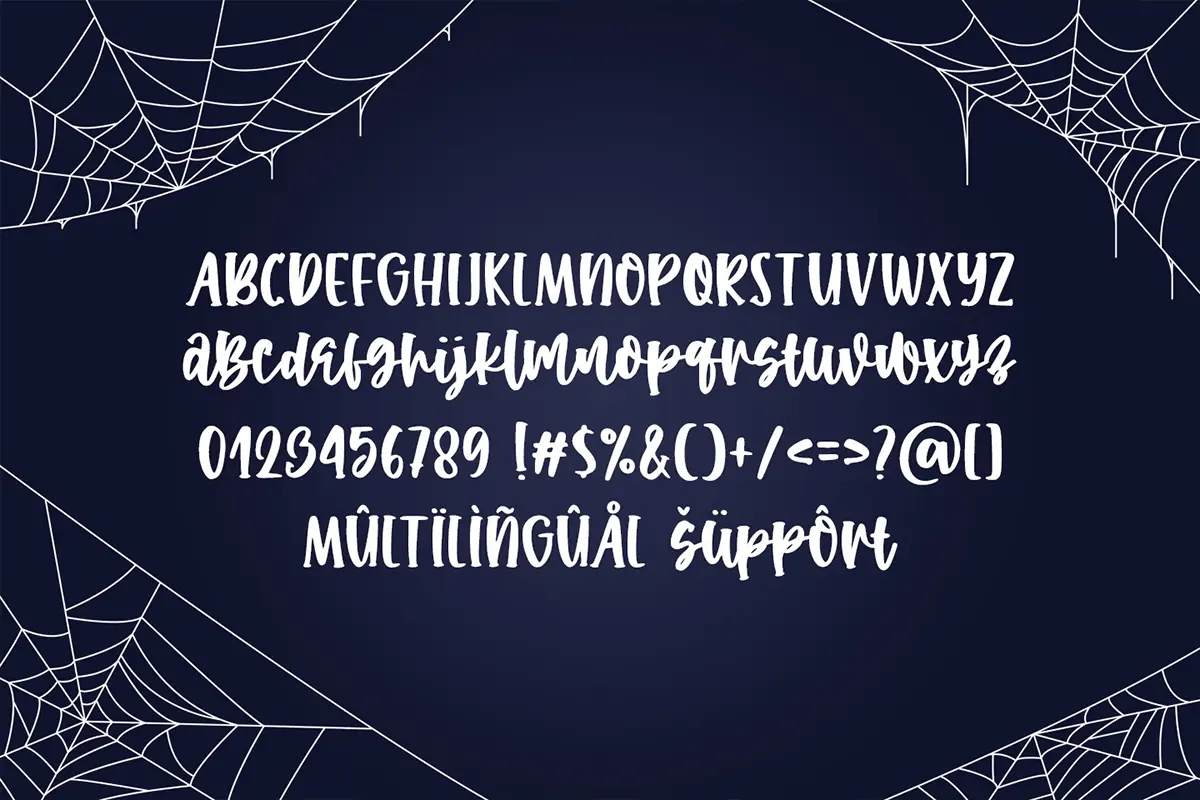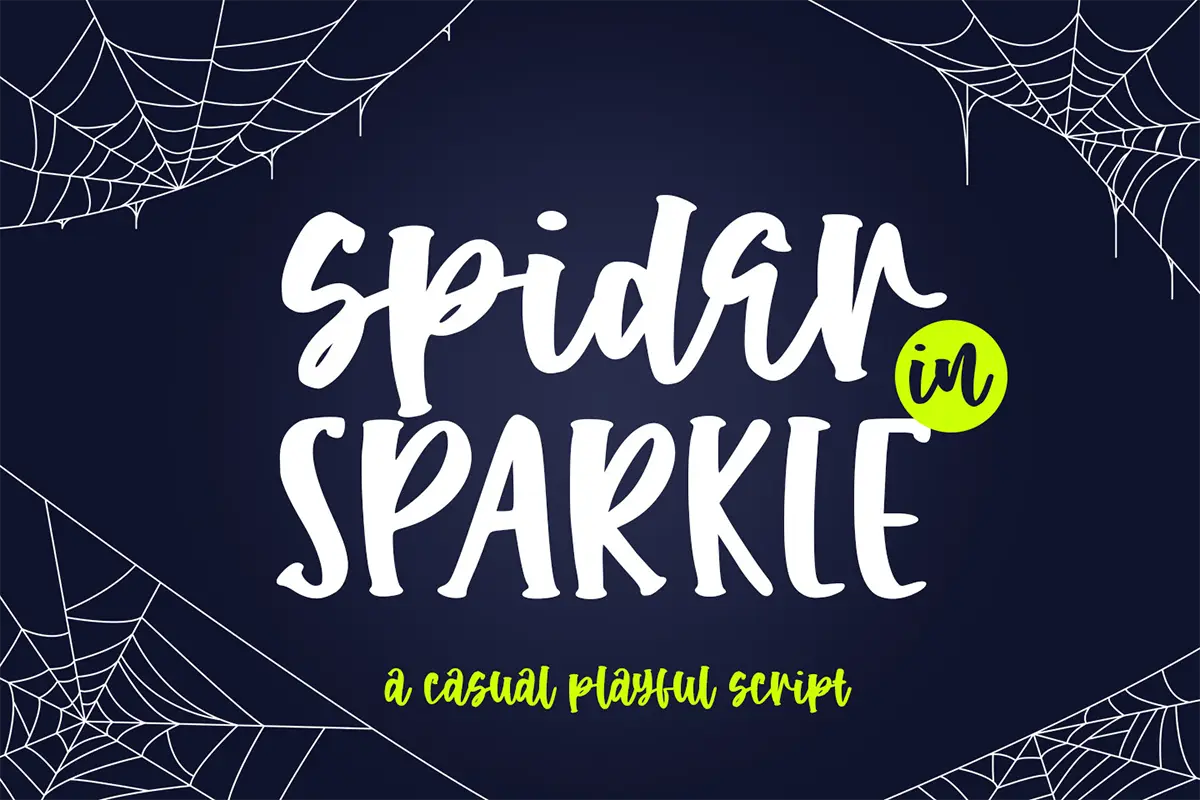
فونت دستنویس Spider in Sparkle
فونت Spider in Sparkle یک فونت دستنویس خنک، راحت و بازیگوش است که به هر طراحی حالوهوایی دوستانه و غیررسمی میبخشد. این فونت برای پروژههایی که نیاز به لمس شخصی و سبک آزاد دارند، انتخابی عالی است و میتواند هر اثر شما را ارتقا دهد.
⭐ ویژگیهای محصول
- سبک دستنویس کژوال و سرگرمکننده
- مناسب برای لوگوهای خلاقانه
- کاربردی در کارتهای تبریک و دعوتنامهها
- عالی برای پستهای شبکههای اجتماعی
- قابل استفاده در طراحیهای هنری و شخصی
🎯 موارد استفاده
- طراحی لوگوهای دوستانه و غیررسمی
- ساخت کارتهای تبریک و یادداشتهای شخصی
- استفاده در پستهای تبلیغاتی و سرگرمکننده
- افزودن حس بازیگوش و خلاقانه به پروژههای گرافیکی